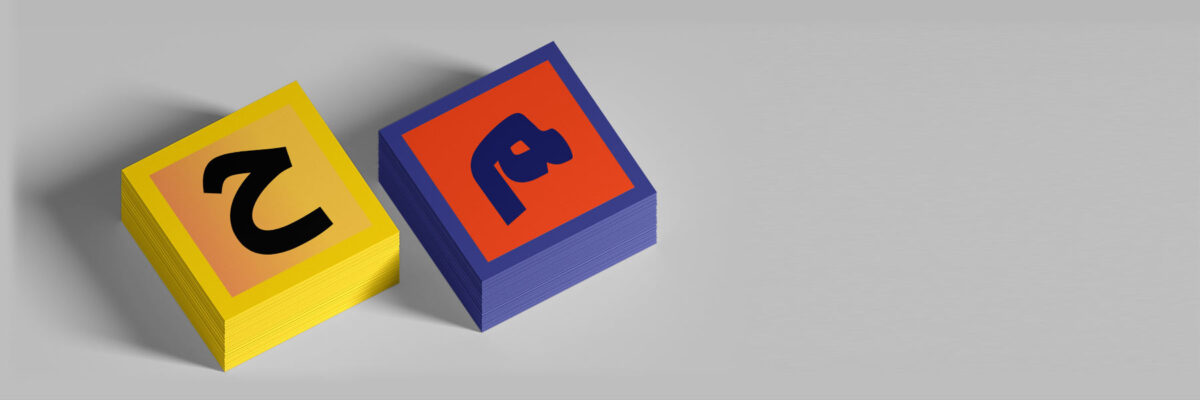
با دستهبندی فونتها در فونتایران آشنا شوید.
فونتهای مختلف میتوانند به لحاظ سبک طراحی یا کاربردشان دسته بندی شوند اما آنجا کار سخت میشود که طراحان تایپ سعی میکنن مرزها را بشکنند و سبکهای مختلف طراحی را ترکیب کنند. یا فونتهایی که میتوانند کاربردهای مختلف داشته باشند
مشکل بعدی اینه که در رابطه با فونت فارسی تا کنون دسته بندی استانداردی انجام نشده. در فونت لاتین استانداردهای دستهبندی وجود دارد اما منطبق با تایپ فارسی نیست.
ما در فونتایران با توجه به تجربه ۱۰ ساله کار با انواع فونت و آشنایی با نیاز کاربرانمان دستهبندیهایی را تعریف کردهایم. در ادامه ویژگی هر دسته بندی را توضیح میدهیم تا منظور ما از عناوین تخصصی را بهتر متوجه شوید.
فونتهای متن / فونتهای عنوان
برای انتخاب فونت اولین سوالی که باید جواب دهید این است: فونت را برای متنهای ریز و طولانی میخواهید یا برای متنهای کوتاهِ تبلیغاتی؟ برای همین ما بطور کلی و از همان ابتدا فونتها را به دو دسته زیر تقسیم کردیم.
فونت متن یا عنوان:
فونتهای متن: این دسته فونتها برای این منظور طراحی شدهاند که در عین زیبایی و خاص بودن بهراحتی خوانده شوند. مطمئنا خواندن هر فونتی در سایز بزرگ راحت است، اما منظور ما از خوانایی روانخوانی در متنهای ریز و طولانی است. مانند پارگرافهای کتاب، وبلاگ، زیرنویس فیلم و … این فونتها معمولا ساده هستند و بافت کلی نوشتار در آنها مهمتر از شکل حروف است.
فونتهای عنوان: این دسته فونتها معمولا شکل حروف خلاقی دارند و خودنمایی میکنند. فرمهای متفاوت و جذابِ این فونتها باعث میشود سریعتر و بیشتر دیده شوند. این فونتها مهمولا دارای وزنهای سنگین یا ترکیبات متنوع هستند و در طراحی انواع تبلیغات استفاده میشوند.
نکته: اکثر فونتهای متن دارای چند وزن سنگین و نمایشی نیز هستند که میتوان از آنها در طراحی عنوانهای نمایشی استفاده کرد.
سبک طراحی:
در دسته بندی ساختاری، فونتها را بر اساس سبک طراحی دسته بندی میکنیم.
هر کدام از ۲ دسته (فونتهای متن و فونتهای عنوان) شامل ۴ زیر دسته میشوند.
۱- فونتهای دستنویس ۲- فونتهای نسخ ۳- فونتهای سنس ۴- فونتهای هندسی
فونتهای دستنویس: این دسته فونتها بر اساس یک دستخط ساخته شدهاند. فونتهای دست نویسی که با قلم نازک (خودکار، خودنویس) طراحی شدهاند برای شبیه سازی دستنوشتههای ریز مناسب هستند. (مثال: فونت مانلی). اما دستنویسهایی که با قلم ضخیم ( ماژیک، قلممو، قلمنی) طراحی شدهاند، مناسب عناوین تبلیغاتی هستند. (مثال: فونت جوان)
فونتهای نسخ: خط نسخ برای نگارش و راحت خوانی کتاب قرآن ابداع شد. با پیدایش صنعت چاپ، ساختار کلی حروفچینی فونتهای عربی و فارسی هم بر اساس خط نسخ طراحی شد. فونتهای دسته نسخ با وجود سادگی و خوانایی همچنان حس و حال خوشنویسی را در خود حفظ کردهاند. این فونتها متناسب با قلم خطاطی، دارای تناوب ضخامت و نازکی هستند. فونتهای دسته نسخ مناسب موضوعات فرهنگی هستند. موضوعاتی که وجود حس انسانی در آنها مهم است. انواع محتوا و تبلیغاتی که در حوزه علوم انسانی قرار میگیرد ترجیح میدهند از فونتهای دسته نسخ استفاده کنن. (ادبیات، هنر، تاریخ، سیاست و …)
فونتهای سنس: فونتهایی که اسکلت خط نسخ را حفظ میکنند اما از قواعد قلم خطاطی پیروی نمیکنند را با اسم سنس دستهبندی میکنیم. این فونتها معمولاً دارای حداقل تنوع ضخامت هستند. در فونتهای سنس جزئیات تزئینی خط نسخ حذف شده تا سادهتر به نظر برسند. این نوع فونت فارسی میتواند همتای فونتهای Sans Serif در فونتهای لاتین باشد برای همین از نام سنس برای این دستهبندی استفاده کردیم.
فونتهای هندسی: فونتهای این دسته، هندسه منحصر به فرد خودشان را دارند. تناسبات، نحوه گردش قلم و بطور کلی شکل حروف در فونتهای هندسی تابع خوشنویسی و نحوه نگارش سنتی نیست. فونتهای هندسی میتوانند بسیار خاص و خلاق باشند اما معمولاً خوانایی کمی دارند و مناسب متن ریز و طولانی نیستند.
دسته بندی کاربردی:
یکی آسانترین روشها برای رسیدن به فونت مناسب این است که آنها را بر اساس کاربردشان دستهبندی کنیم.
فونتهای مناسب رابط کاربری: فونتهای مناسب طراحی وب و نرم افزار لازم است ساده و خوانا باشند. اندازه صفحه نمایش موبایل و گجتهای همراه کوچک است و نوشتهها لازم است در اندازه ریز و شرایط نوری مختلف حداکثر خوانایی را داشته باشند. فونتهای دسته سنس معمولا بهترین گزینه برای استفاده در طراحی رابط کاربری هستند.
فونتهای مناسب مطبوعات: در مطبوعات متنها معمولا طولانی هستند و برای همین خوانایی و روانخوانی اهمیت زیادی دارد. مطبوعات چاپی مانند کتاب، روزنامه و مجله بیشتر در زمینه علوم انسانی فعالیت دارند و تمایل دارند از فونتهایی استفاده کنند که دارای حس و حال فرهنگی و رسمی است. فونتهای دسته نسخ بیشترین استفاده را در تایپوگرافی مطبوعات چاپی دارند.
نکته: نرم افزارها و رابط کاربریهایی که دارای موضوعات فرهنگی هستند یا میخواهد رسمی باشند ممکن است فونتهای دسته نسخ را ترجیح دهند. در مقابل مطبوعات چاپی دارای موضوعات مدرن و تجاری نیز فونتهای سنس را مناسب کار خود میدانند.
فونتهای مناسب تبلیغات: طراحی پوستر، بیلبورد، بستهبندی، سردر فروشگاه و … اقلام تبلیغاتی محسوب میشوند. نوشتهها در گرافیک تبلیغاتی معمولا کوتاه هستند و بیشتر از خوانایی، خاص بودن و جلب توجه فونت اهمیت دارد. فونتهای ویژه عنوان معمولا مناسب استفاده در تبلیغات هستند.
امکانات و ویژگیها:
علاوه بر دستهبندی ساختاری و کاربردی، فونتها بر اساس ویژگیها و امکاناتی که دارند هم دستهبندی شدهاند. هر نوع ویژگی و قابلیتی که بتوانیم تعدادی از فونتها را در آن بگنجانیم به این لیست اضافه خواهد شد.
فونتهای متغییر: وریبل فونتها (Variable fonts) نسل جدید از فرمت نرمافزاری در فونت هستند. در فونت متغییر حروف می توانند نازک و ضخیم شوند، کشیده و فشرده شوند، شکل نقطهها تغییر کند و … همه این امکانات در یک فایل فونت وجود دارد و دیگر شما نیازی به فایلهای متعدد برای تغییر وزن و استایل ندارید. تجمیع همه وزنها و استایلها در یک فایل باعث میشود سرعت لود وبسایت شما کاهش یابد. در حال حاضر بیشترین کاربرد فونت متغییر در طراحی وبسایت است.
فونتهای تزئینی: فونتهایی که دارای نقوش و جزئیات تزئینی و الحاقی باشند را در این دسته بندی قرار میدهیم. این دسته فونتها گاهی متاثر از خطوط تزئینی گذشته هستند که در آراستن بناها و اشیاء استفاده میشده اند.
فونتهای خوشنویسی: فونتهایی که با هدف بازسازی یکی از خطوط خوشنویسی گذشته طراحی شده اند را در این دسته قرار میدهیم. فونتهای خوشنویسی شخصیت تصویری و نمایشی قوی دارند و به دلیل ترکیبات فراوان ساخت نرم افزاری آنها پیچیده است.